El pasado 17 y 18 de mayo, tal y como aquí os presentábamos, tuvieron lugar en Granada las jornadas tipográficas “Tipos de Interés” con conferencias y workshops de primer nivel.
Con un especial reconocimiento al trabajo desempeñado en la región, Granada Tierra Soñada inauguraba las Jornadas. Vanesa Aguilera y Sergio Arredondo mostraron a los asistentes el enfoque y desarrollo de la Granaina Font, un proyecto que recoge la peculiar tipografía plasmada en las calles del Albaicín. Matizaron la importancia de potenciar la cultura del diseño y la formación con el fin de que las ideas evolucionen.
Por su parte, Elena Veguillas (editorial Tipo e) con su ponencia “Recetario del Joven Tipógrafo”, además de definir extensamente el mundo tipográfico y establecer distinciones entre conceptos tales como fuente, caligrafía, y lettering entre otros, introdujo al público en el ámbito legal que atañe a la tipografía: la controvertida temática de las licencias, que muchos usuarios ignoran.
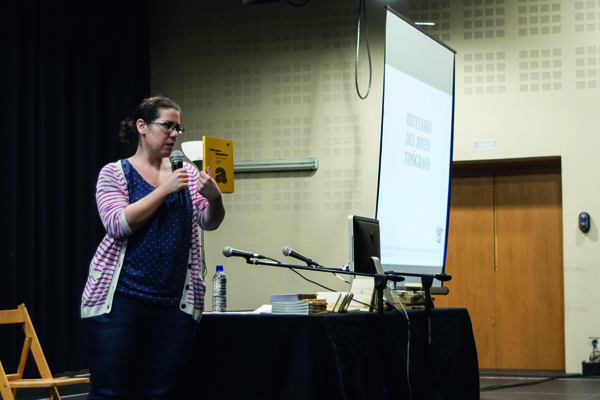
El diseñador portugués André Beato dio a conocer su fórmula de trabajo basada en la inspiración más que en el proceso, y que él mismo concibe como un juego tipográfico. Realizó una trayectoria por sus referentes y tendencias más notorias, incidiendo en la cultura hip hop, la década de los 80, y el trabajo gráfico desempeñado por su padre. Destacaba su admiración por lo realizado a mano, y aconsejaba a los estudiantes de diseño a jugar con todo lo que quisieran . Entre sus creaciones además de destacar las realizadas para grandes marcas como Montana, Nike, Converse, o Ronaldo, mostraba proyectos personales como Lisborn Lovers.
La Familia Plómez, una asociación cultural surgida en Madrid, concluía la sesión del viernes dando a conocer el eje central de su trabajo: letterpress, o impresión tipográfica. En a penas un año de recorrido han logrado conseguir “grandes tesoros” de la imprenta artesanal, entre ellos la “Super Veloz” diseñada por Joan Trochut y fundida en los 40s. Con su charla “Pa habernos matao” Roberto Gamonal y Juan José López, relataban su experiencia y las anécdotas más significativas en el proceso de formación de “la familia”, la búsqueda de maquinaria y materiales necesarios para la composición en plomo.
La sesión del sábado fue inaugurada por el estudio barcelonés Toormix, representado por el tándem creativo compuesto por Oriol Armengou y Ferrán Mitjans. Ambos expusieron su propio enfoque del diseño a través de consejos, entre los que cabe señalar: “no somos artistas”, “hay que dedicarle tiempo a las ideas para poder avanzar a nivel conceptual”, “No te acomodes, sé autocrítico”, y “trabaja con humor”, entre otros. Con un especial énfasis entre tipografía y branding, mostraron sus nuevos proyectos muy vinculados a la ciudad de Barcelona.
El reconocido disenador y tipografo Enric Jardi, a traves de su ponencia “Por qué las letras son así”, nos sumergió en la historia de la tipografía desde sus orígenes, siguiendo su evolución a través de cada cultura y civilización.
Para concluir, Ricardo Rousselot deleitó a los asistentes con toda una vida de trabajo dedicada íntegramente a la caligrafía: “Elegí mi camino desde muy joven y me decanté por la letra”.
En horario de mañana se llevaron a cabo una serie de talleres, entre los que destacaron el de Tipos móviles, impartido por el impresor local Paco Vela, y el de Cronología del tipo, a mano del maestro Ricardo Rousselot en el que todos pudieron disfrutar de las habilidades que posee este reconocido calígrafo.
Tipos móviles
Cronología del tipo
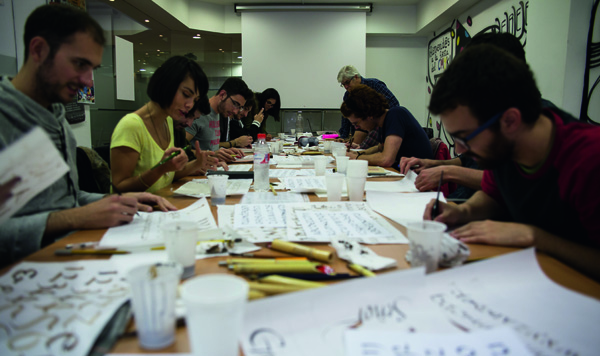
Además, los talleres de Estampatipos, Tipos árabes, Tipos con papel, y Estos tipos son la caña también tuvieron una gran acogida, y todos los asistentes pudieron divertirse y aprender de las agradables mañanas tipográficas.
Estampatipos
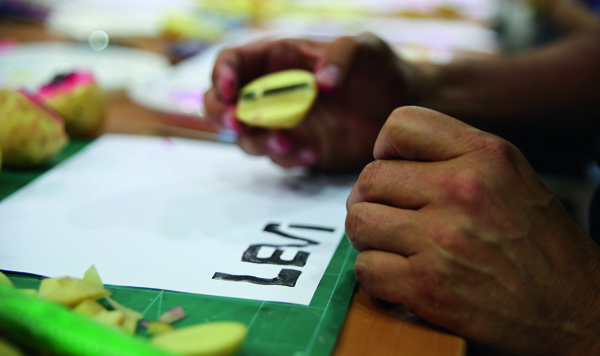
Tipos árabes
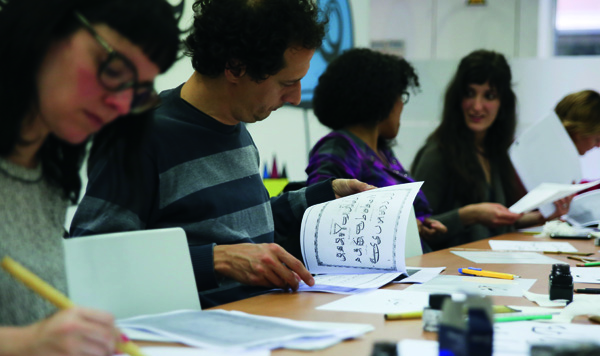
Tipos con papel
Estos tipos son la caña